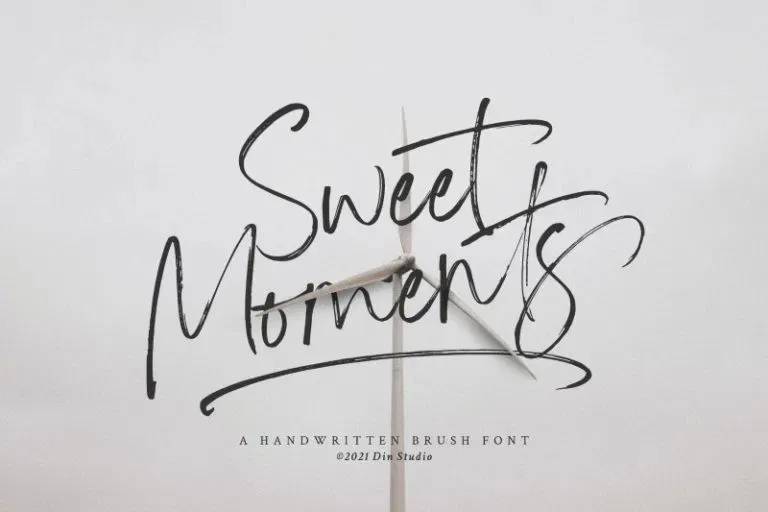
Sweet Moments Font – Download Grátis
Esta nova fonte script chamada Sweet Moments foi criada pelo Din Studio, trazendo uma personalidade muito profunda e sofisticada. Ela captura a essência do luxo e elegância, um toque de paixão embutido em cada curvatura e torsão da fonte desenhada à mão. Utilize-a para headlines, logotipos, cartões de visita, citações impressas, convites de todos os tipos, cartões, embalagens, sua marca no site ou redes sociais, e você certamente verá seu negócio se beneficiar com seus melhores impressiones. Com muitas opções para versão com swash, essa fonte ganha um toque ainda mais especial.